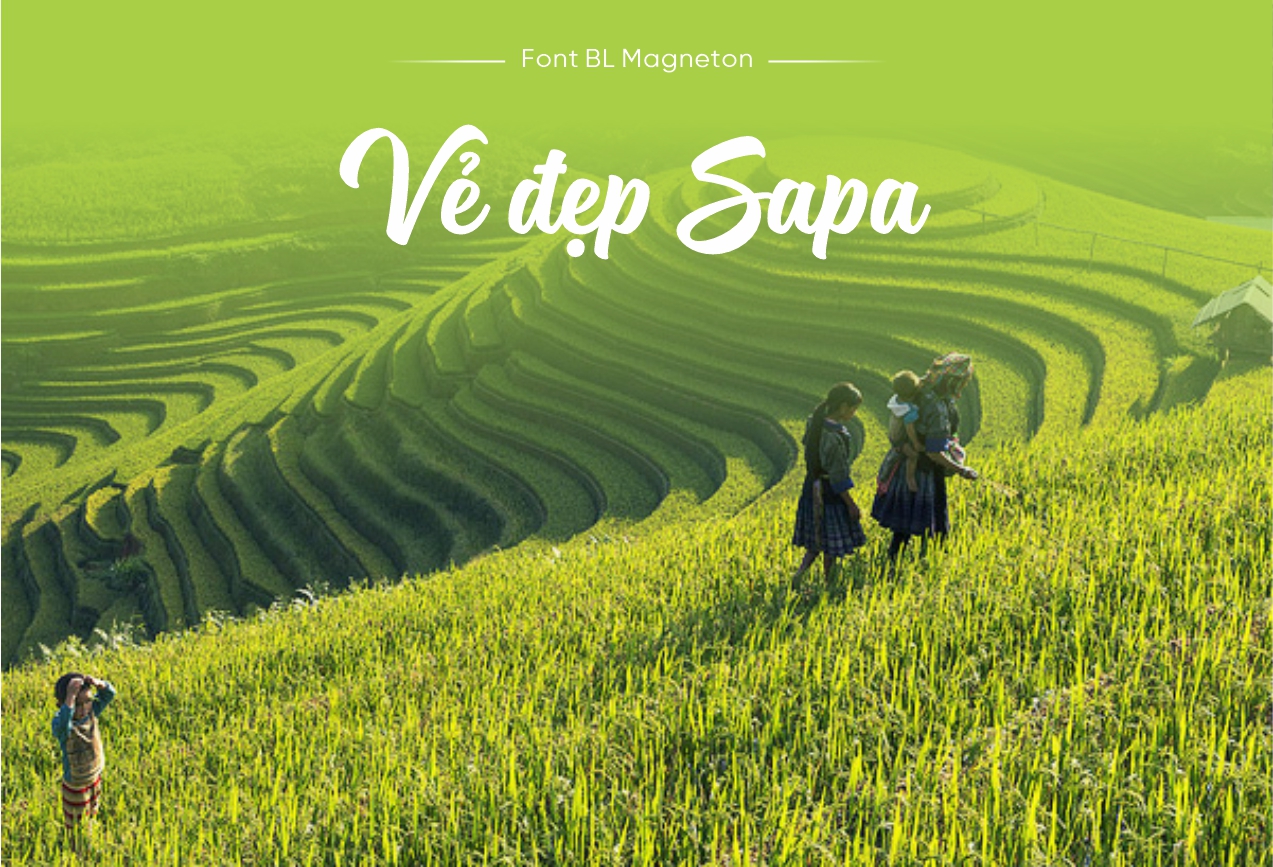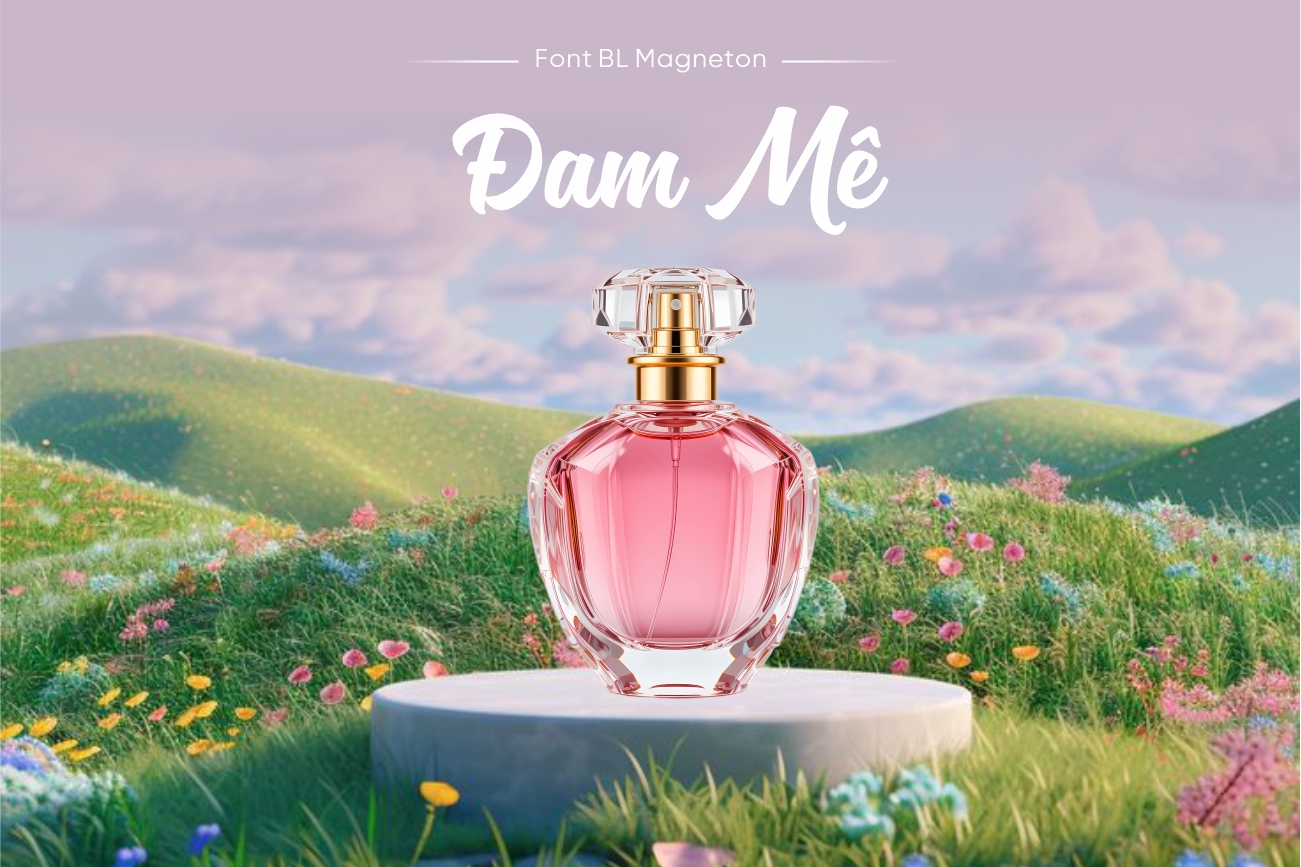
Font Viết Tay BL Magneton – Font Brush Việt Hóa Thanh Lịch
Nếu bạn đang tìm kiếm một font viết tay mềm mại, uyển chuyển nhưng vẫn giữ được sự sang trọng trong thiết kế, thì BL Magneton chính là lựa chọn lý tưởng. Đây là bộ font mang hơi thở hiện đại, được thiết kế theo phong cách font brush với những nét cọ mềm mại, tự nhiên như được vẽ bằng tay. Nhờ vậy, mỗi dòng chữ đều toát lên sự gần gũi, tinh tế và đầy cảm xúc.
BL Magneton được phát triển với 3 phiên bản trọng lượng (Bold – Regular – Light), giúp người dùng linh hoạt trong nhiều dự án khác nhau. Kiểu Bold dày dặn, mạnh mẽ rất phù hợp cho tiêu đề, poster hoặc logo cần sự nổi bật. Trong khi đó, bản Regular cân đối và dễ đọc, thích hợp cho nội dung trung tính, còn Light thanh mảnh, bay bổng lại cực kỳ phù hợp cho thiệp mời, trích dẫn nghệ thuật hay các ấn phẩm lãng mạn.
Điểm cộng lớn nhất của BL Magneton là đã được Team BL Việt hóa tỉ mỉ, hỗ trợ đầy đủ tiếng Việt cùng hệ thống dấu thanh chuẩn đẹp. Điều này giúp các nhà thiết kế có thể ứng dụng linh hoạt trong mọi bối cảnh, từ poster quảng cáo, bao bì mỹ phẩm, thương hiệu thời trang, đến các thiết kế về hoa tươi hay du lịch.
Với sự kết hợp giữa phong cách font viết tay tự nhiên và chất liệu font brush hiện đại, BL Magneton không chỉ mang lại tính thẩm mỹ cao mà còn tăng sự cá nhân hóa cho tác phẩm. Đây thực sự là một trong những font Việt hóa đáng để bạn thêm vào bộ sưu tập thiết kế của mình.